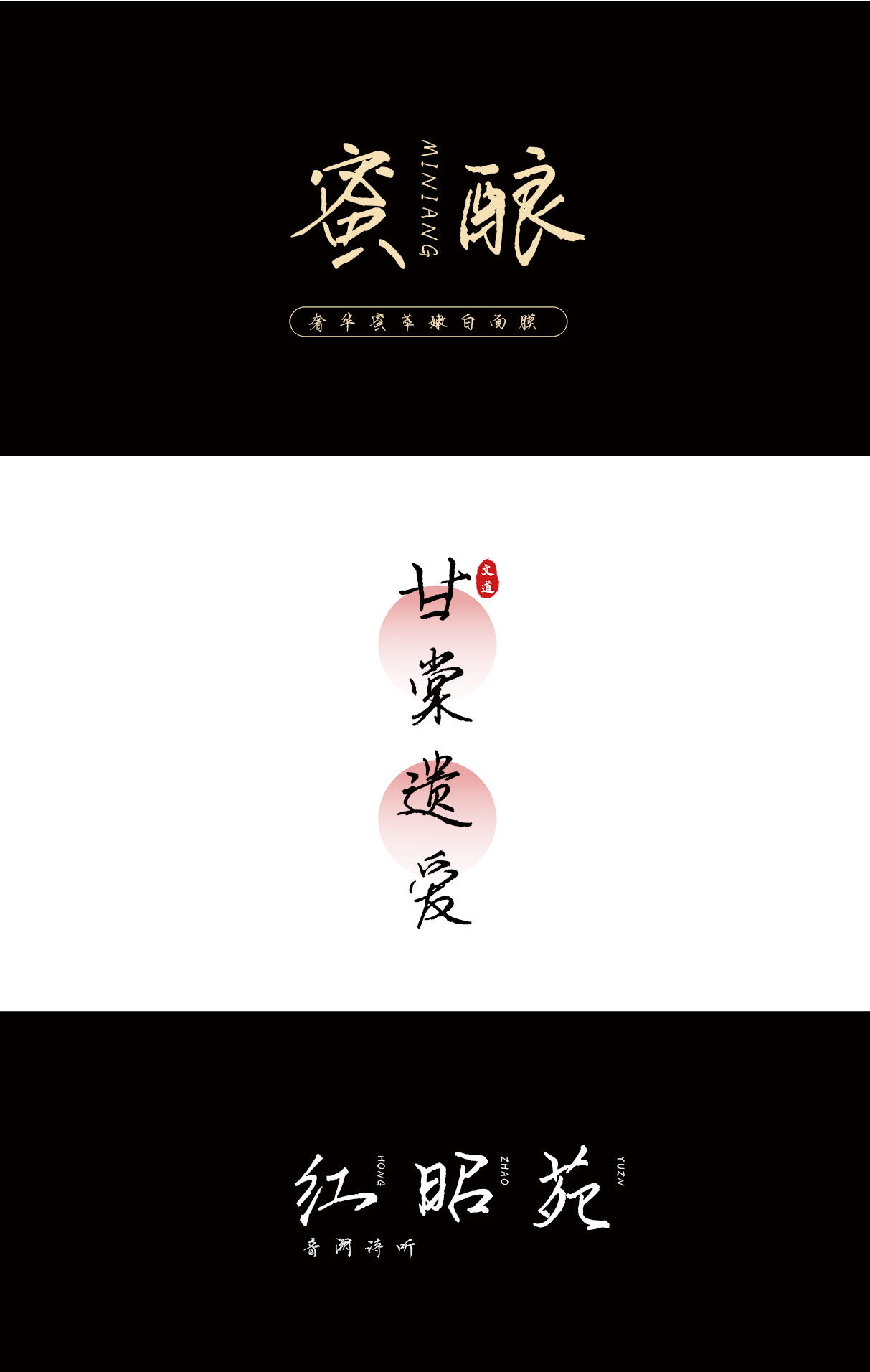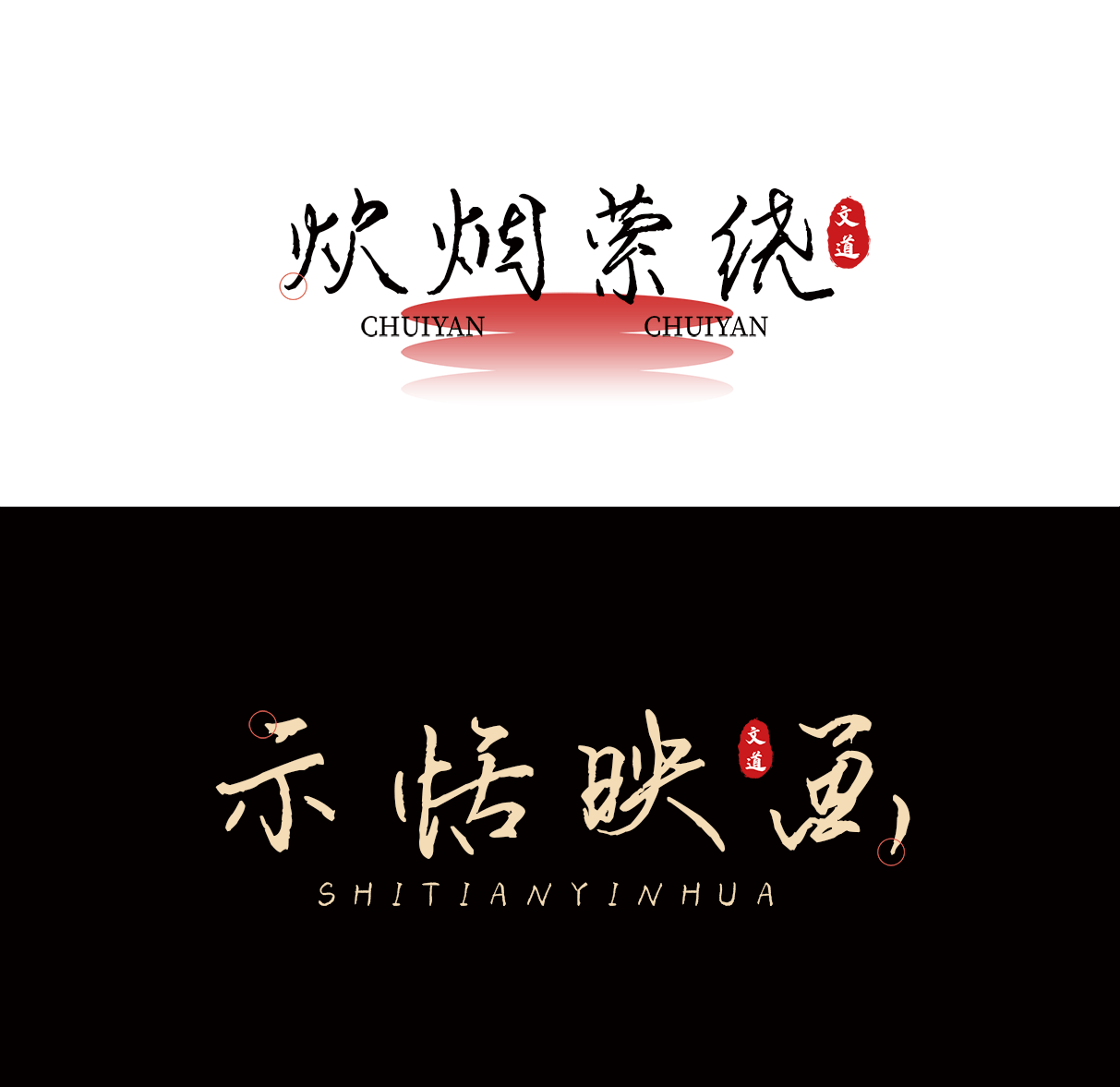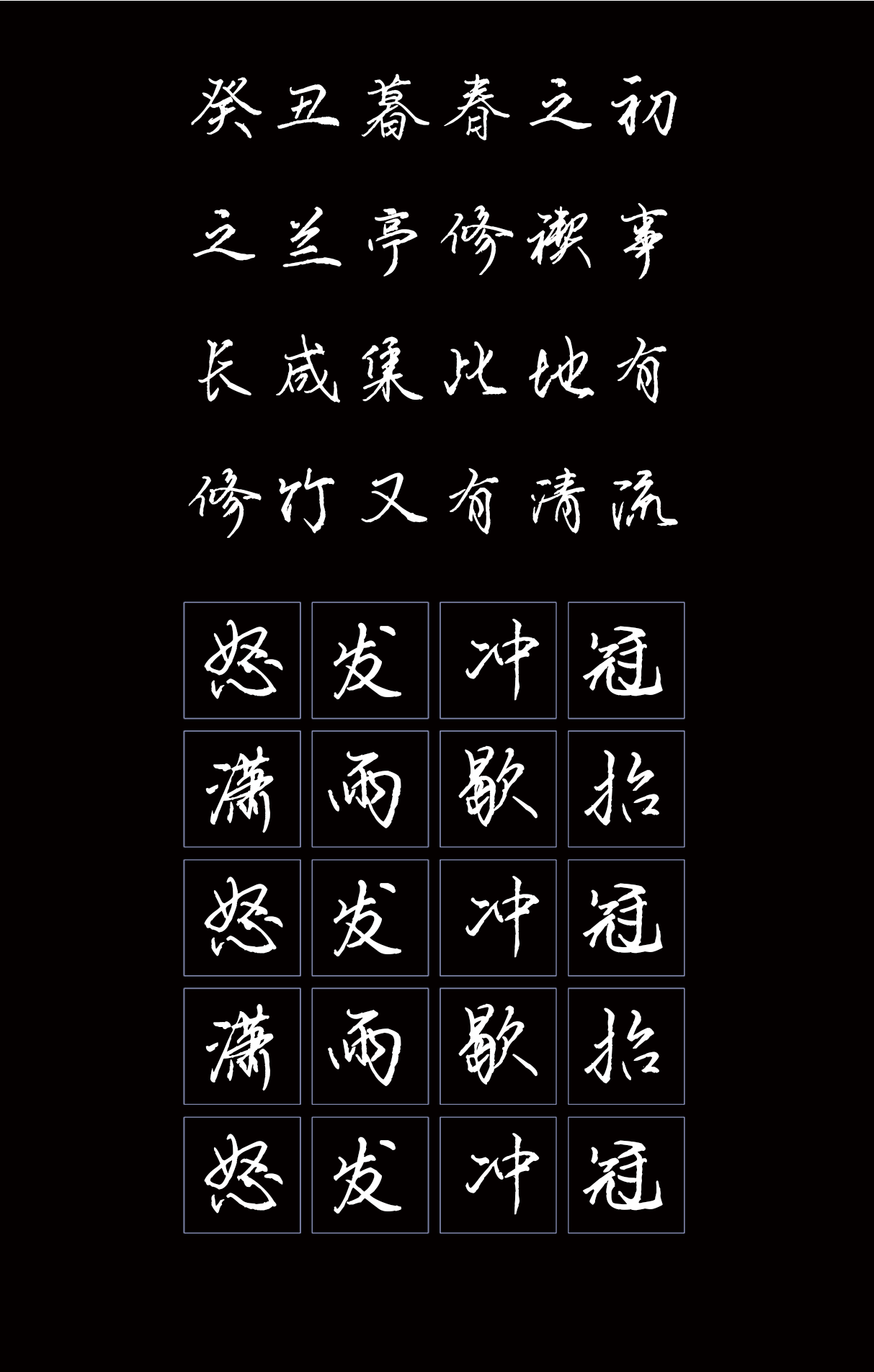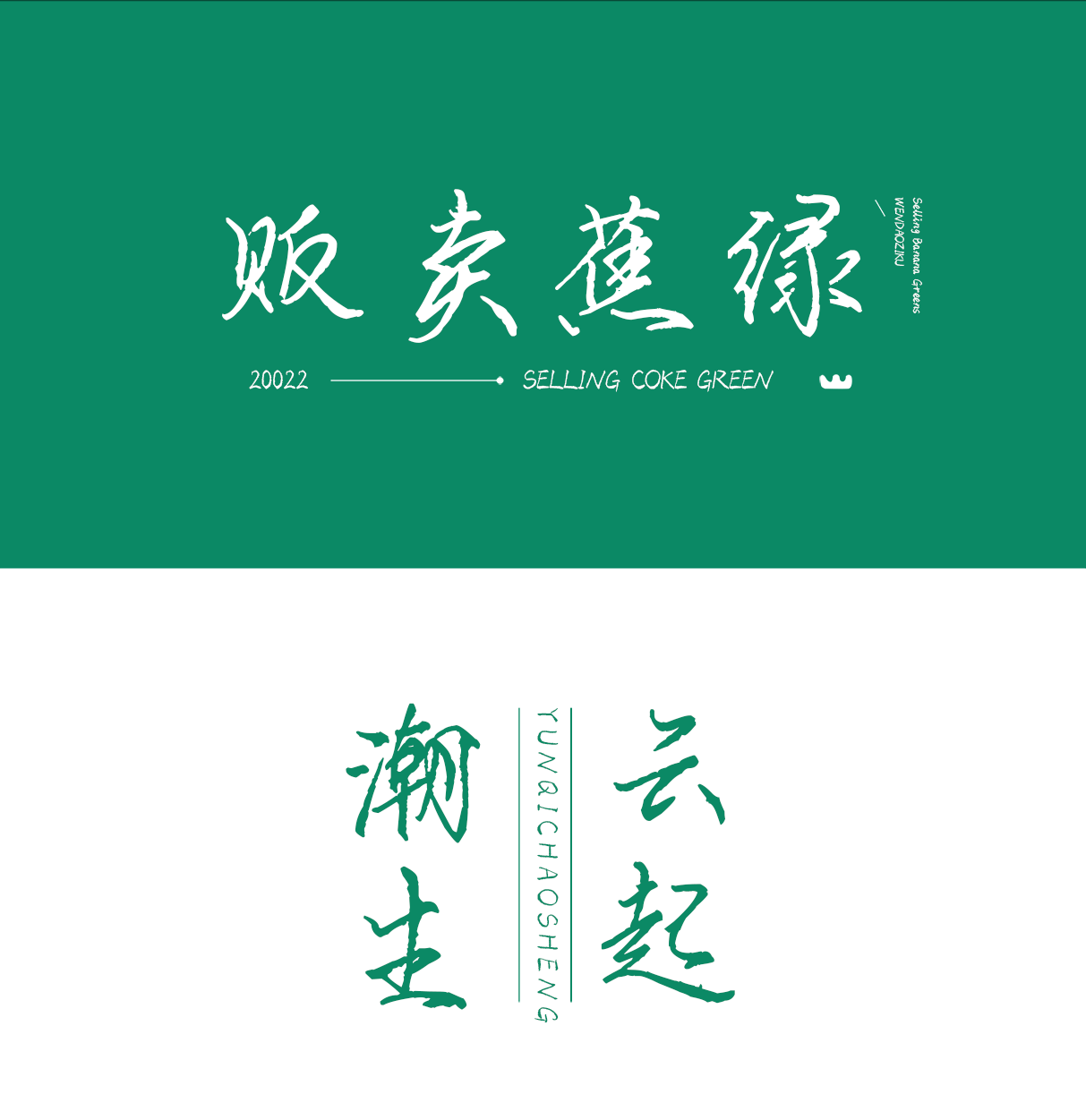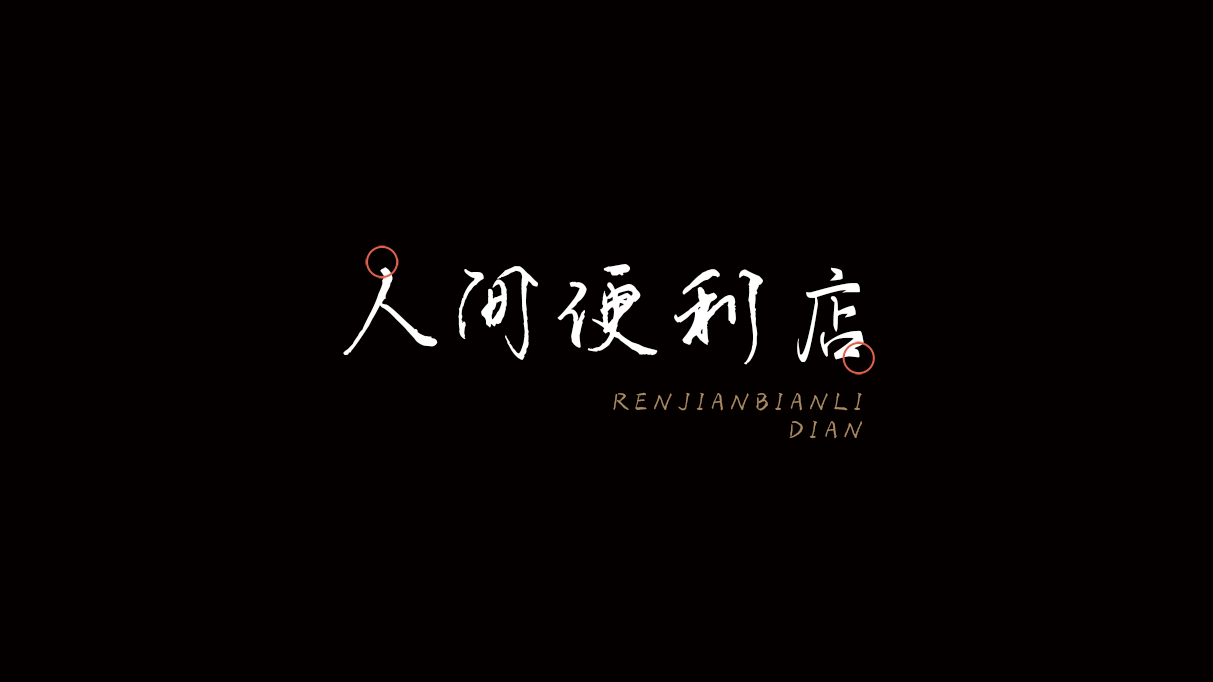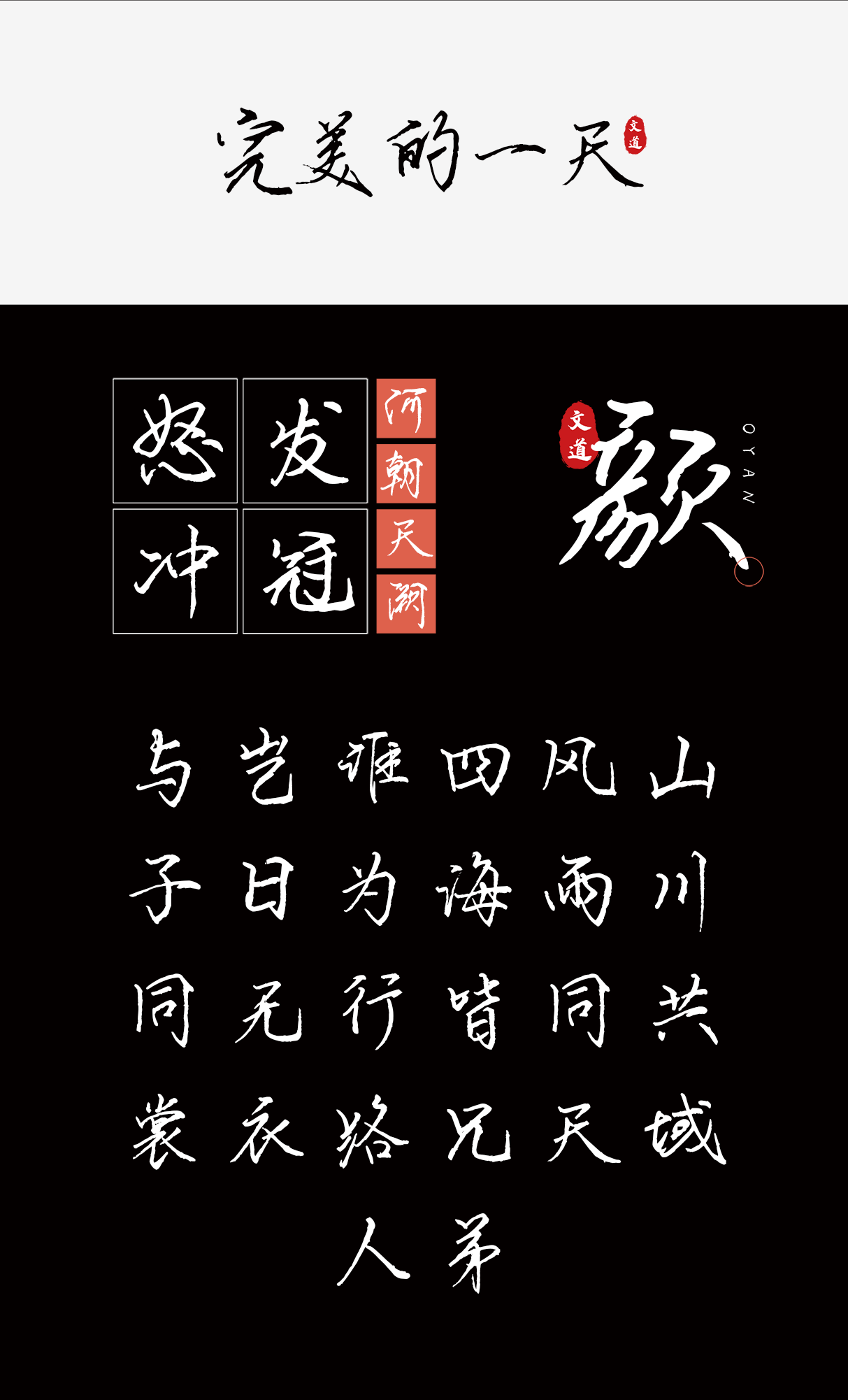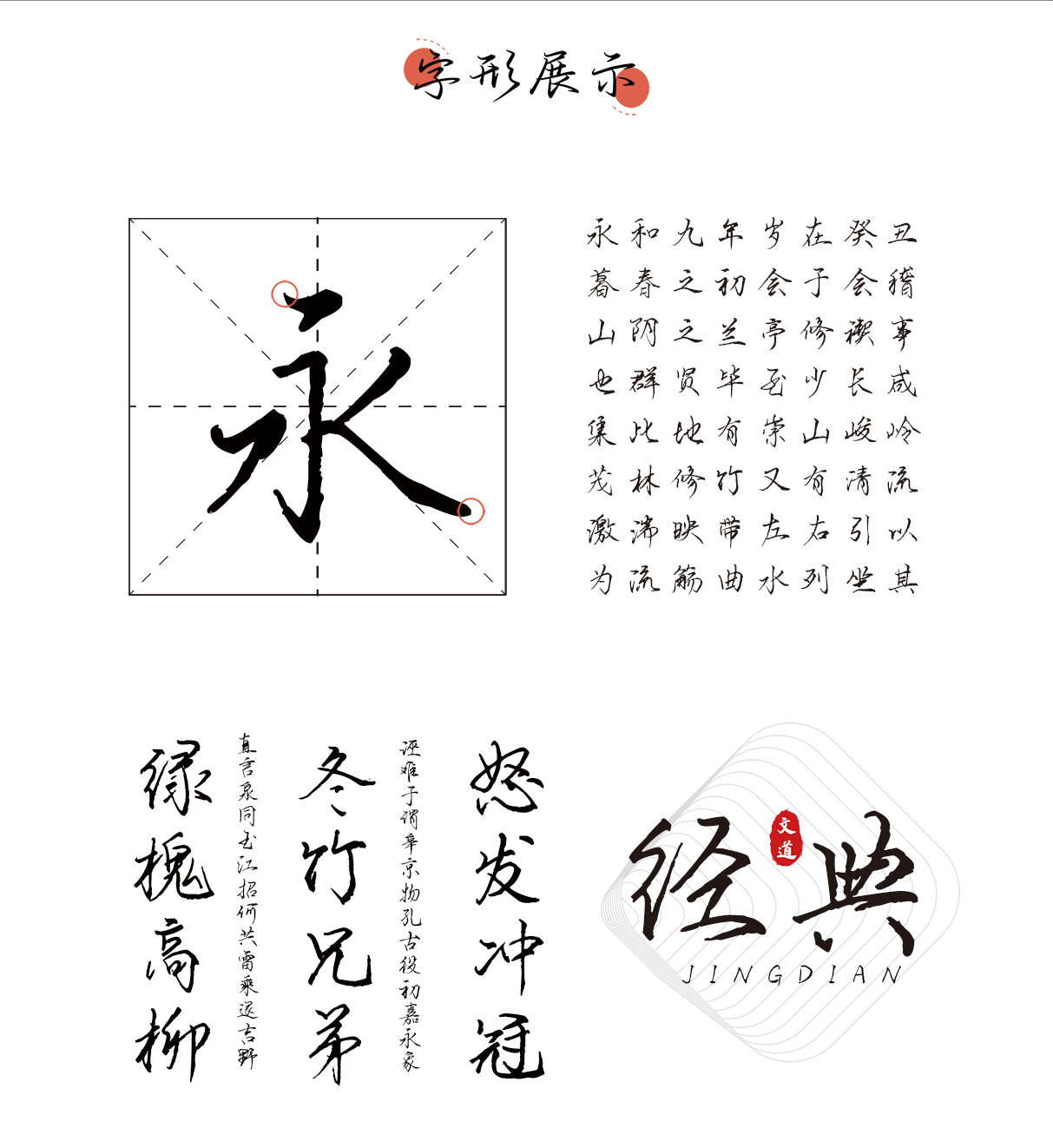
人间便利店
文亦有道,笔墨添香;墨韵飞扬,意蕴绵长。
字体名称: 人间便利店
简介: 人间便利店笔画刚硬锐利,笔触狂放,字形浑厚洒脱,且结构多变。不仅适用于横向、纵向的排版,还方便了字与字之间的穿插。在继承传统的同时又融入当今商业化的应用,适合于电影海报、包装、品牌名称、各类商业海报、户外广告标题等。